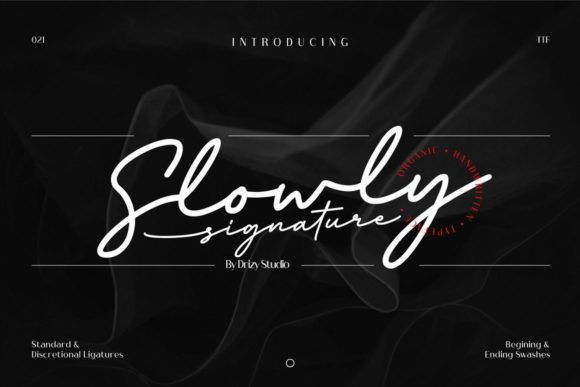
Slowly Signature
- это прекрасный и неподвластный времени рукописный шрифт.
Это лучший выбор для создания привлекающих внимание логотипов, брендинга и цитат.
Slowly Signature закодирован PUA, что означает, что вы можете легко получить доступ ко всем глифам и штрихам!